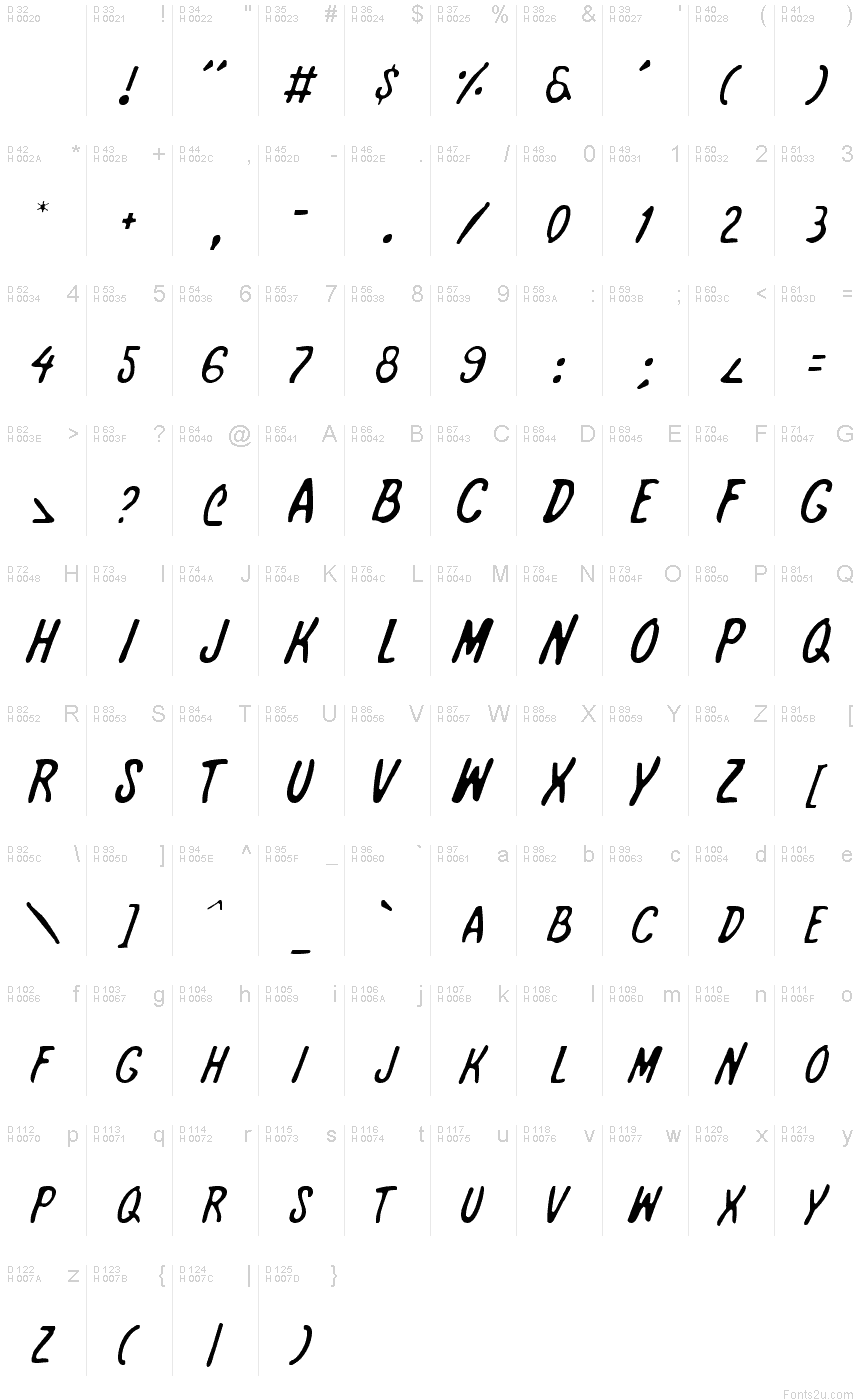
International Super Hero Light di Iconian Fonts è un font display gratuito in stile fumetto che sprigiona tutta l'energia dei supereroi. Le sue lettere alte e inclinate sembrano tracciate con un pennarello a punta grossa; i tratti leggermente irregolari donano un senso di velocità e movimento, come gli effetti sonori che esplodono tra le vignette di un fumetto. La texture è audace e intensa, ma rimane sufficientemente leggibile per comporre brevi linee di testo senza risultare confusa.
Con International Super Hero Light, i titoli diventano istantaneamente dinamici e memorabili. È la scelta perfetta per copertine di fumetti, poster di supereroi, inviti per feste di bambini, loghi per videogame, miniature di YouTube e gadget giocosi. Questo font gratuito dà il meglio di sé nei grandi formati, dove il suo stile disegnato a mano può esprimersi al meglio; abbinalo a un carattere sans serif semplice per le didascalie e il testo di supporto, in modo da mantenere i riflettori puntati su quei titoli eroici e d'impatto.
Mappa dei caratteri di International Super Hero Light
Mappa dei caratteri di International Super Hero Light: Latino di base, pagina 1
Glifi del carattere International Super Hero Light — Latino di base, pagina 1